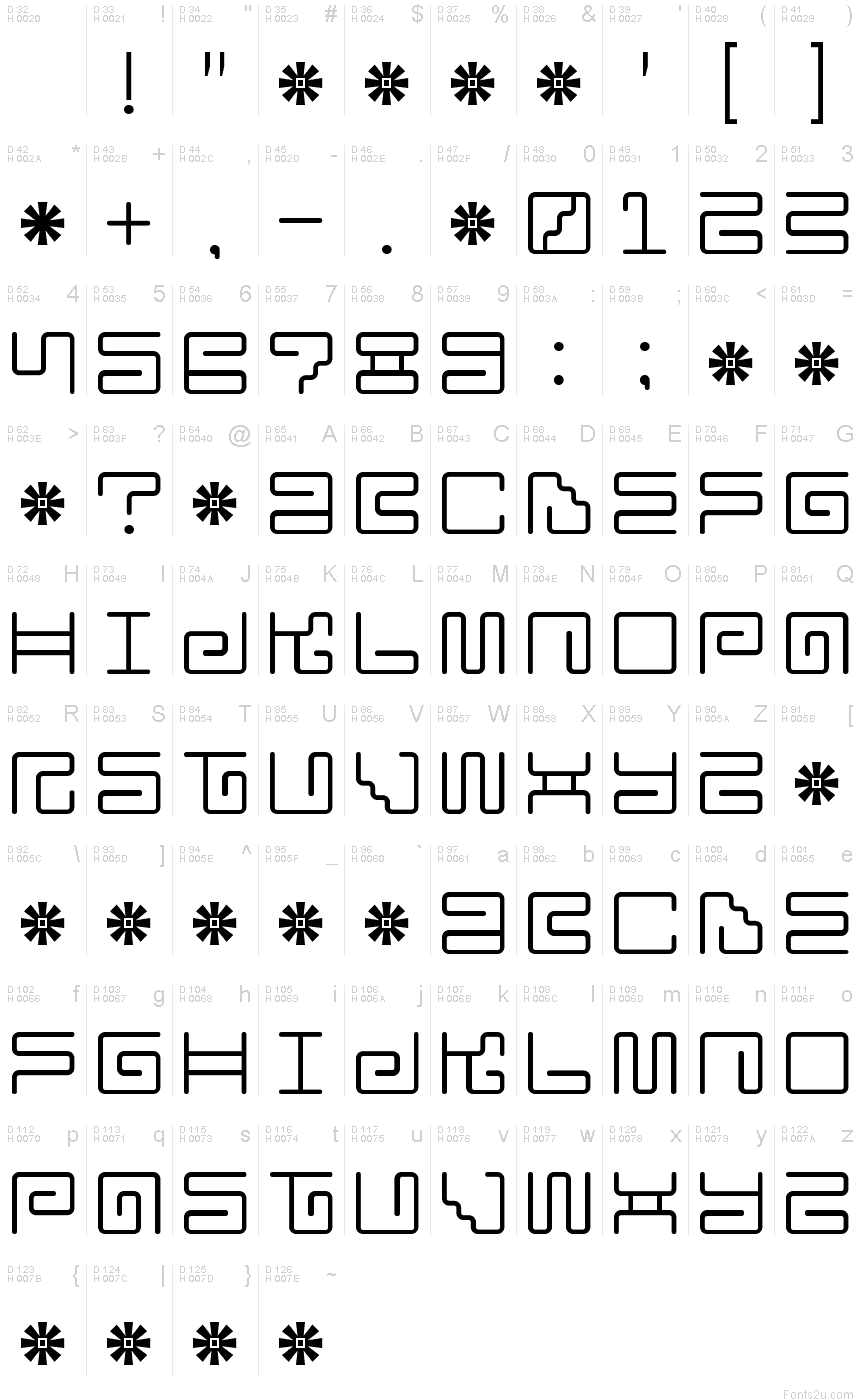
Iron Lounge
Iron Lounge di Jakob Fischer è un carattere display gratuito, dal sapore groovy e futuristico. Con la sua struttura squadrata, gli angoli smussati e i tratti monolineari puliti, ricorda i tubi al neon piegati per creare eleganti insegne da lounge. Le lettere scorrono orizzontalmente con un ritmo rilassato e arioso, conferendo alle parole una presenza fresca e leggera, retro ma al contempo futuristica.
Utilizzando Iron Lounge, i titoli assumono immediatamente un'atmosfera da club sci-fi, perfetta per poster di eventi musicali, copertine di album elettronici, titoli di videogiochi, branding tech e grafiche accattivanti per siti web. Questo font gratuito dà il meglio di sé a grandi dimensioni, dove i suoi rettangoli arrotondati possono davvero respirare; abbinalo a un semplice sans serif geometrico per i testi più piccoli, così da mantenere il focus sulle sue forme levigate e luminose.